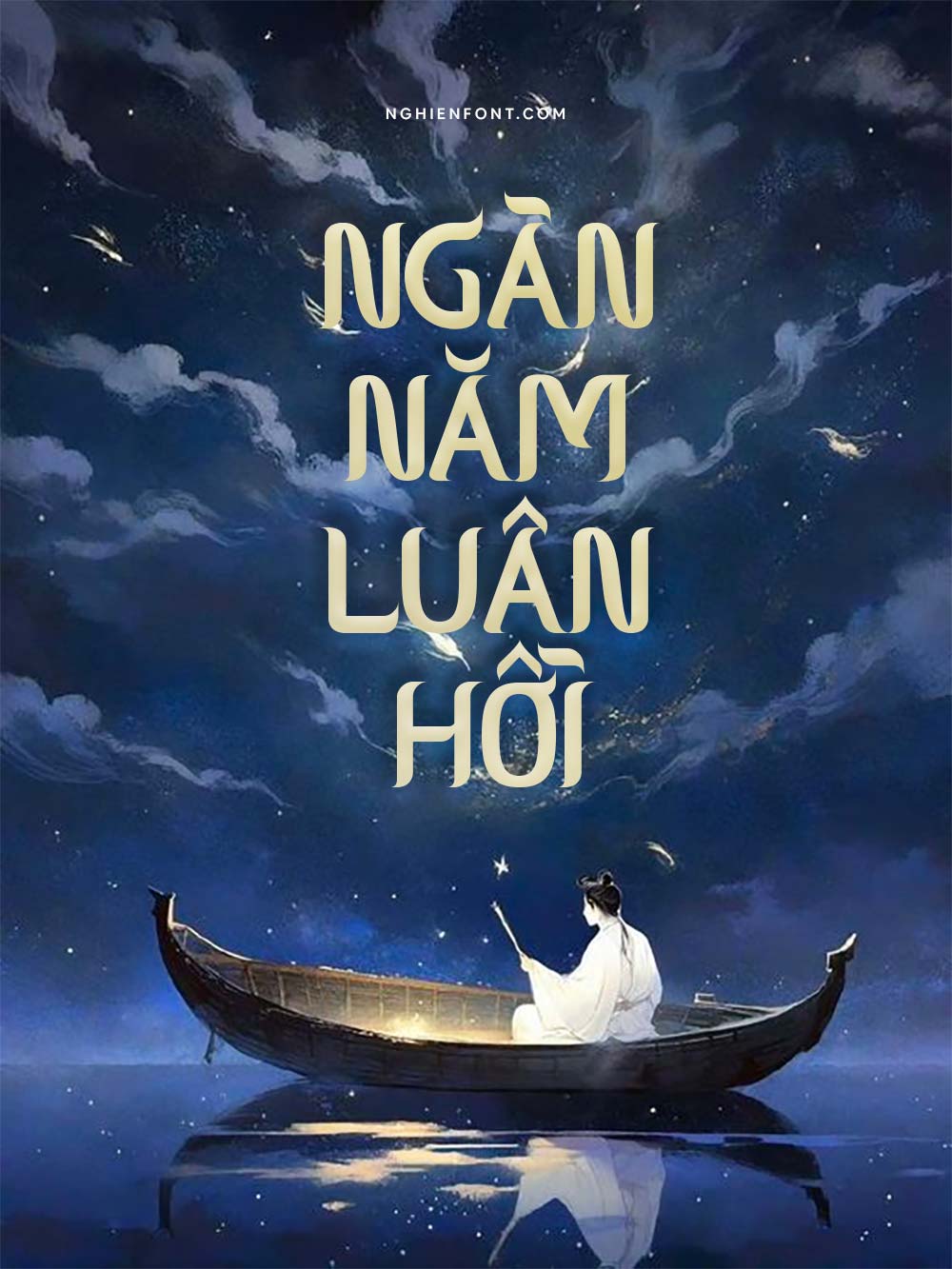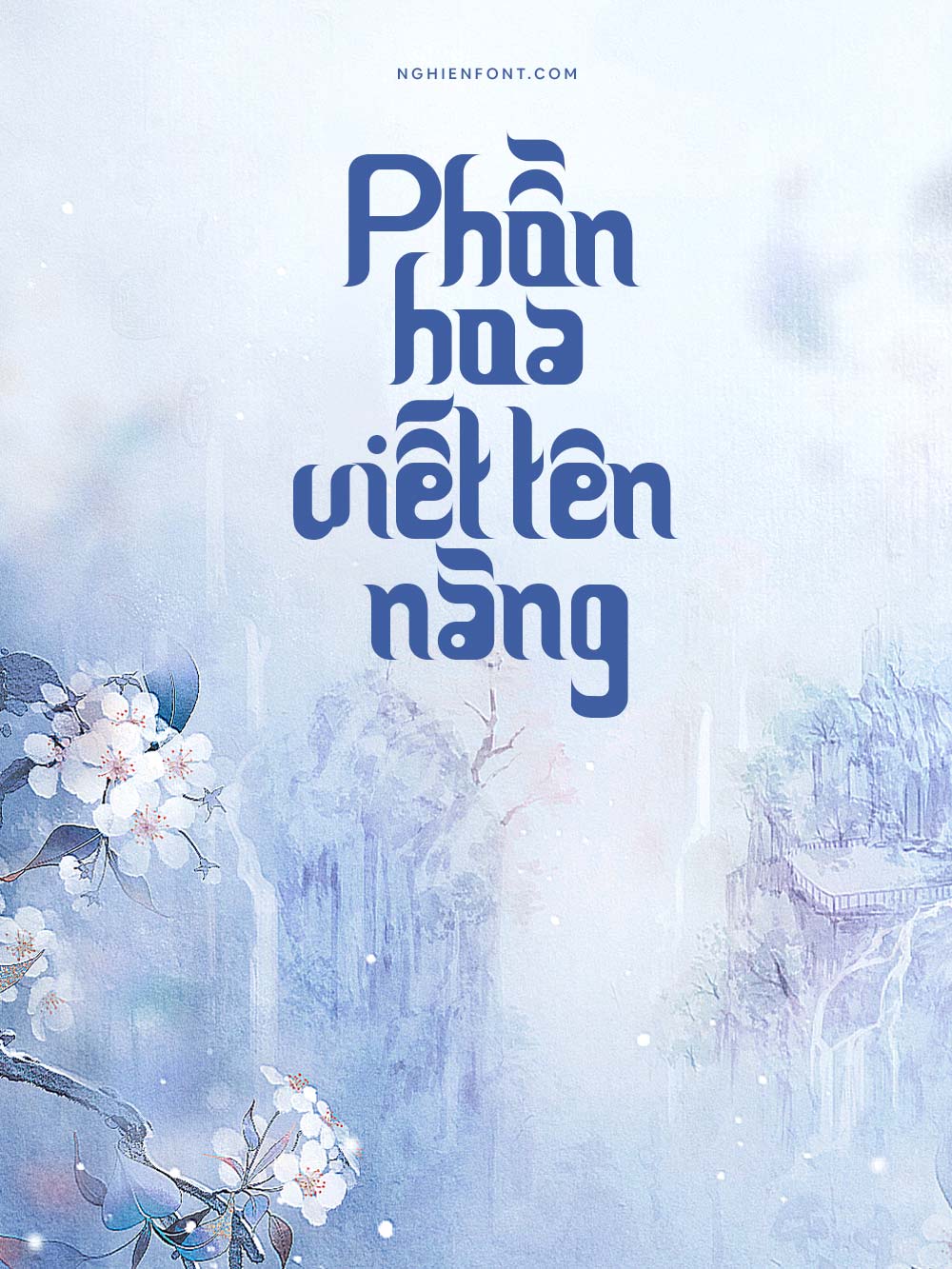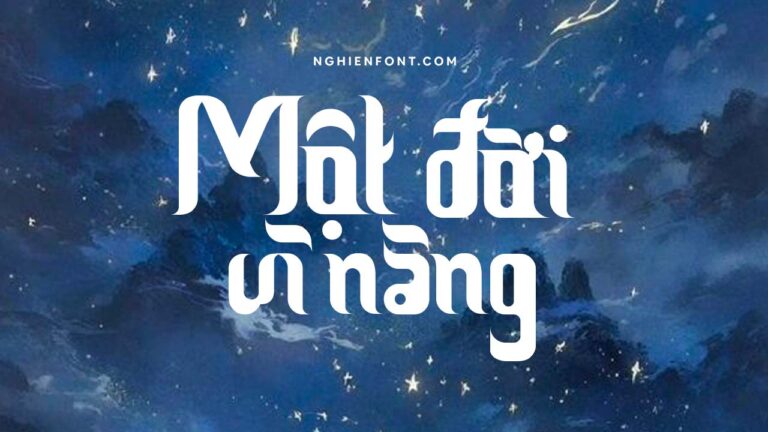
Font việt hóa LNTH Ceria Lebaran, đây là một kiểu font dạng thư pháp với các nét chữ đậm, dày được thiết kế hài hòa mang lại một cảm giác giống như chữ bút lông.
Font Ceria Lebaran rất phù hợp cho các thiết kế cổ trang và hiển thị tốt ở kích thước lớn vì vậy bạn có thể sử dụng font này làm tiêu đề, có thể sử dụng cho nhiều thiết kế như bìa truyện, poster, trang trí…